workshop 'Back to the 80's'
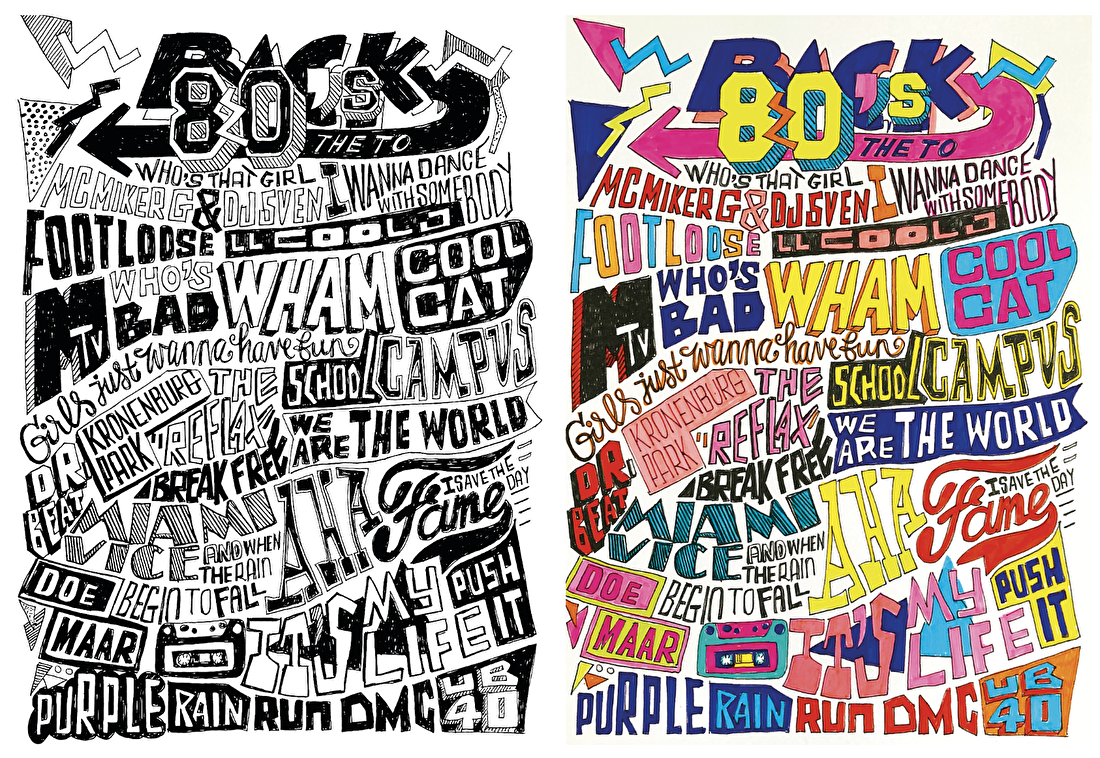
WORKSHOP 'BACK TO THE 80's'
Weet jij nog op welke liedjes je vroeger danste? Naar welke winkels je ging om kleding te kopen die je ouders waarschijnlijk 'afschuwelijk' vonden, de platenzaak waar je lp's en casettebandjes kon kopen? Je weet wel die tijd waarin niet alles beter was, maar anders.
De jaren '80 zijn qua vormgeving een ratjetoe aan stijlen wat weer een jaren '80 vormgeving opleverde. Letters hoefde niet in balans, gebruik van vreemde vormen in neonkleuren en dat gecombineerd met felle kleuren. In deze workshop gaan we weer even terug naar die tijd. We gaan een poster (A4) letteren in de stijl van de jaren '80. Jouw eigen poster, jou muziek (en daar hebben we geen oordeel over!) en alles wat er in je hoofd voorbij komt. Ik leg je iets uit over de letterstijl van toen, dus wat letterteken ervaring heb je wel nodig..... hoewel, eigenlijk gaan we terug naar onze schoolagenda die we volplakten en tekenden met letters! Dus als je nog weet hoe dat ging, doe mee!
We beginnen met het maken van een Header boven aan de pagina, dit doen we gezamelijk maar je bent vrij je eigen vorm daarin te verzinnen. Ik neem je mee in de vormgeving van toen en laat je voorbeelden zien. Uiteraar leg ik ook uit vanuit welke indeling je kunt gaan werken en vertel dan hoe je die typische jaren '80 letters kunt tekenen. Daarna gaat de playlist aan met uiteraard liedjes uit de jaren '80. Je gaat je pagins nu vullen met liedjes, dingen, of woorden die je uit de tijd te binnen schieten! Je gaat vanaf dan wel direct op het papier werken, met eindeloos schetsen ga je het niet redden ;) Kies je voor fineliner in zwart wit? Of liever in kleur? Ik neem naast fineliners ook markers, viltstiften en (last but nog least) higlighters mee!
Iedereen mag meedoen, ook als je niet eens uit de jaren '80 komt, maar wel iets wil leren over die tijd en natuurlijk van die liedjes houd! (daarin ga ik geen consessie doen!)....
Als je eerder mijn workshop 'boodschappenbriefjes' hebt gedaan, kan deze workshop meteen een goede oefening zijn. Maar bovendien is dit apenkooien onder handletteraars....we gaan er gewoon lekker een 'old skool' letterfeest van wil maken! En schroom niet een zweetband om te doen, je plastic arbanden te dragen, je haar te toeperen.... rolschaatsen wel graag thuislaten ;)